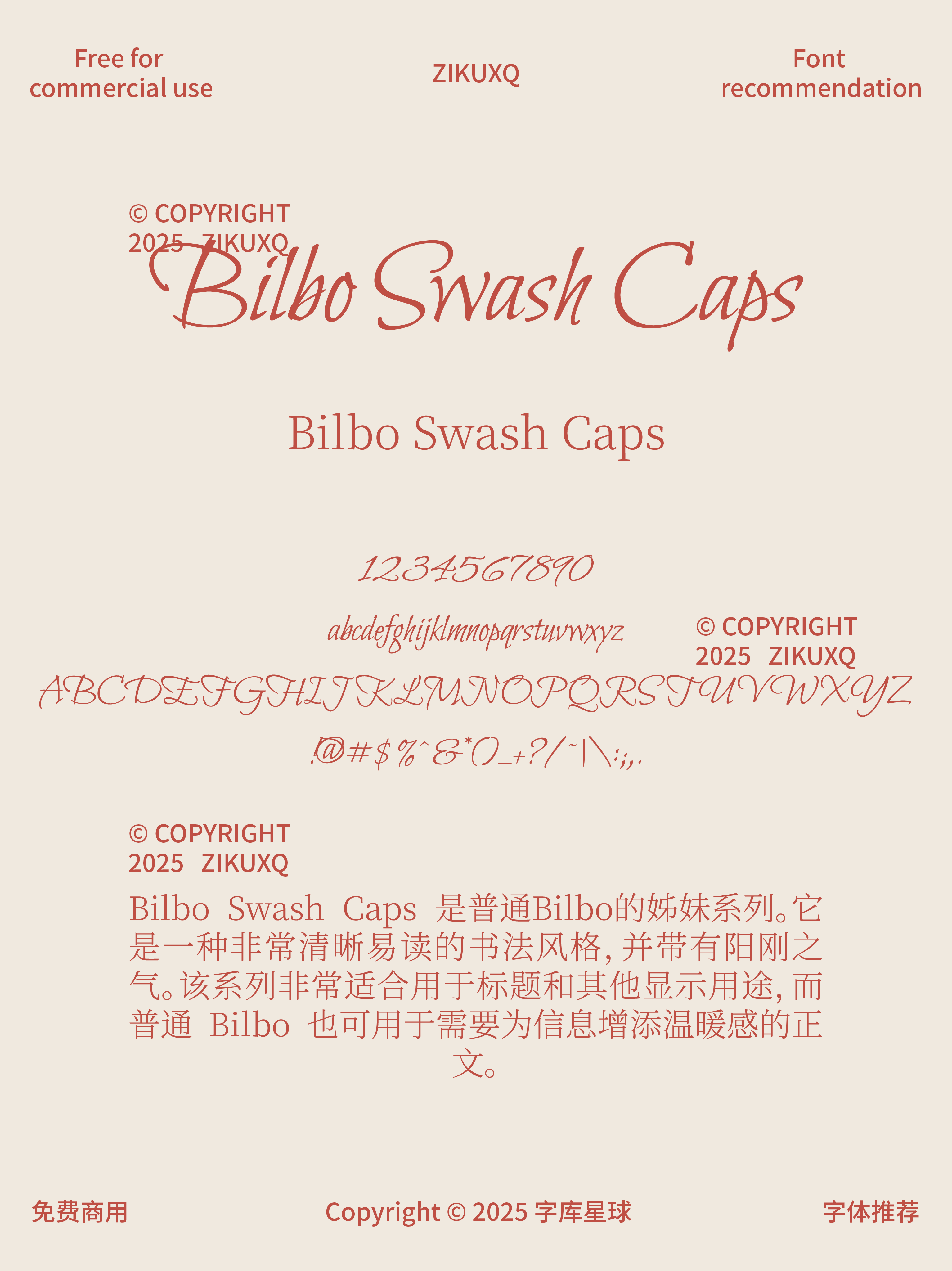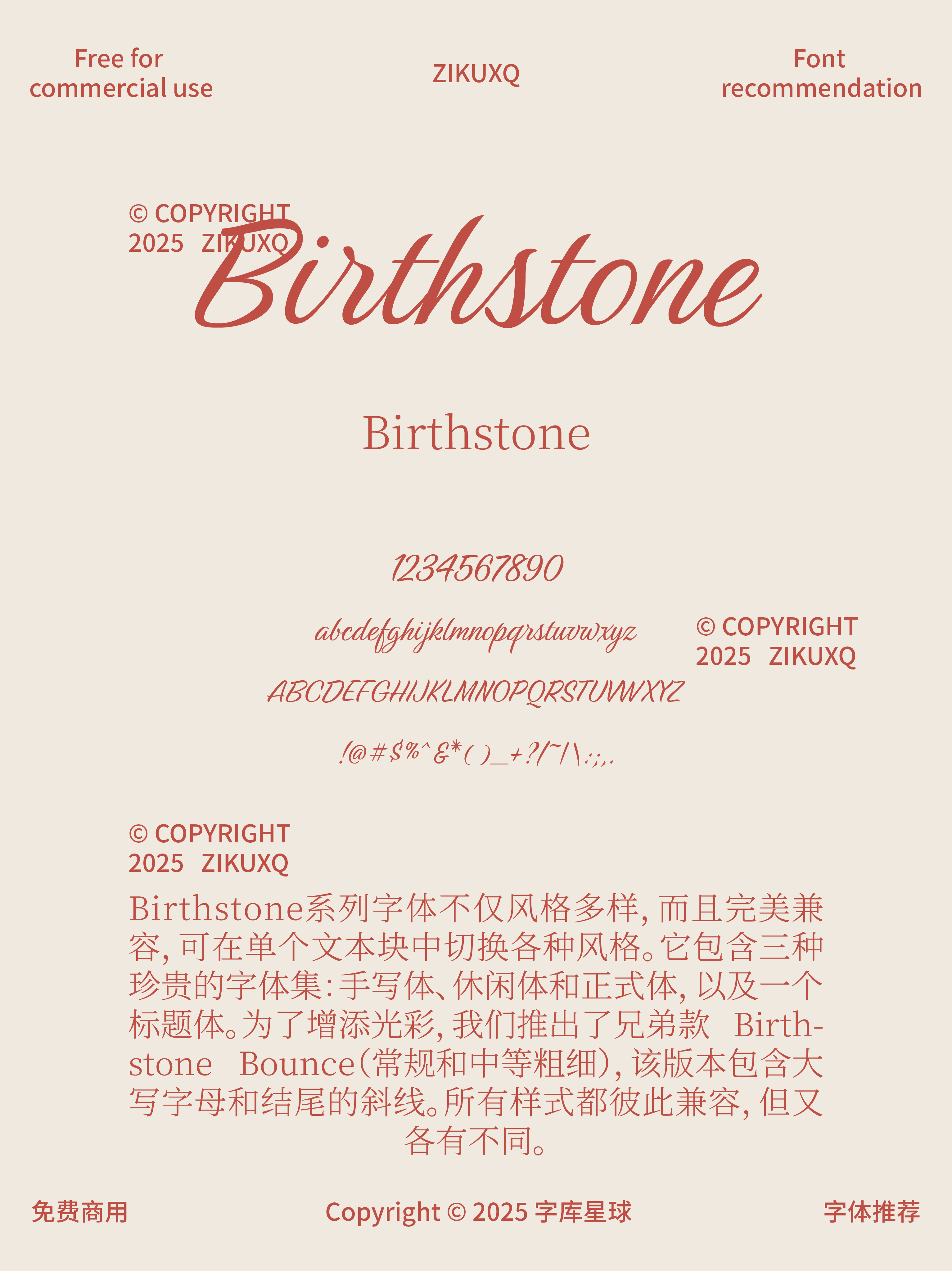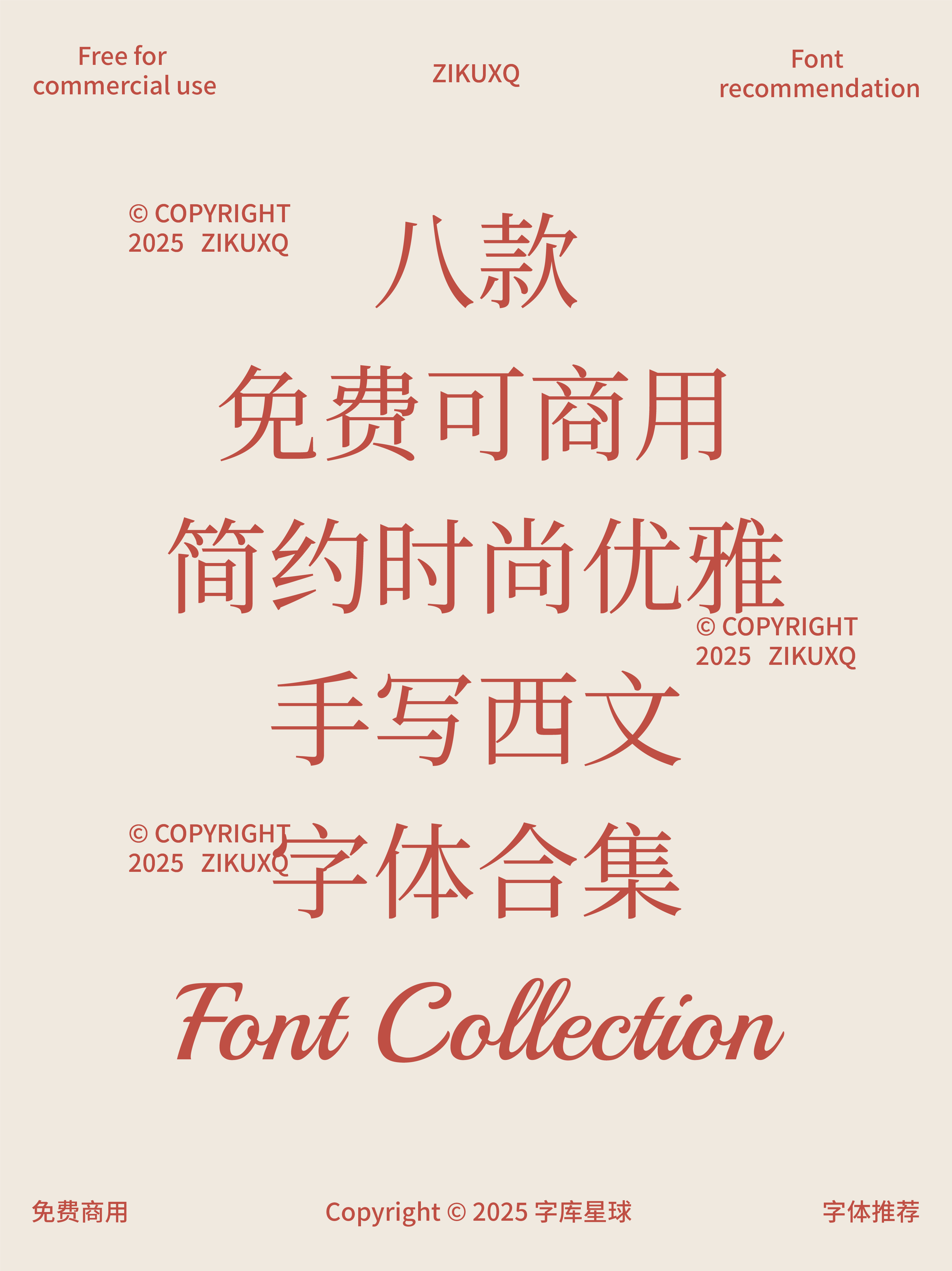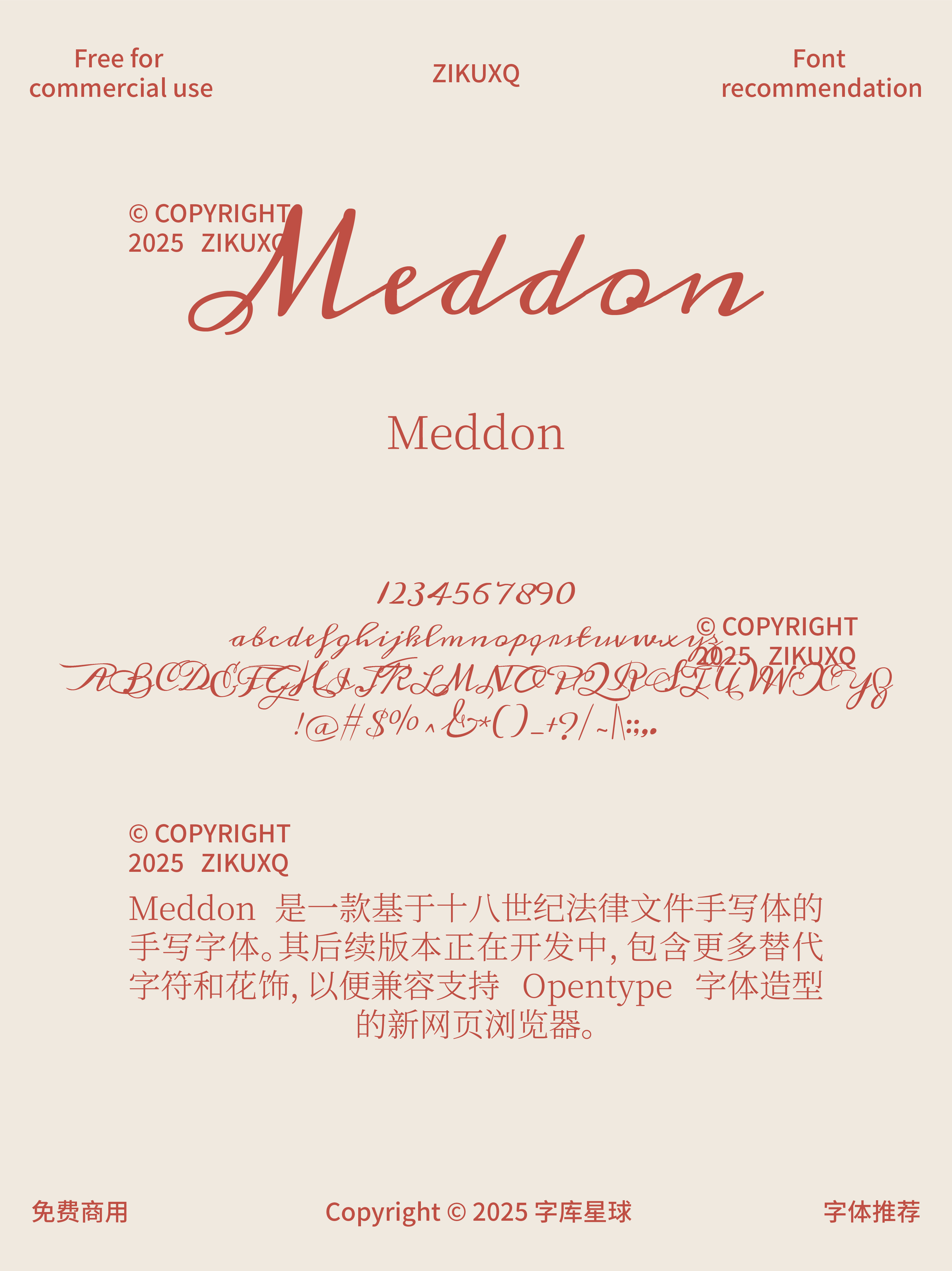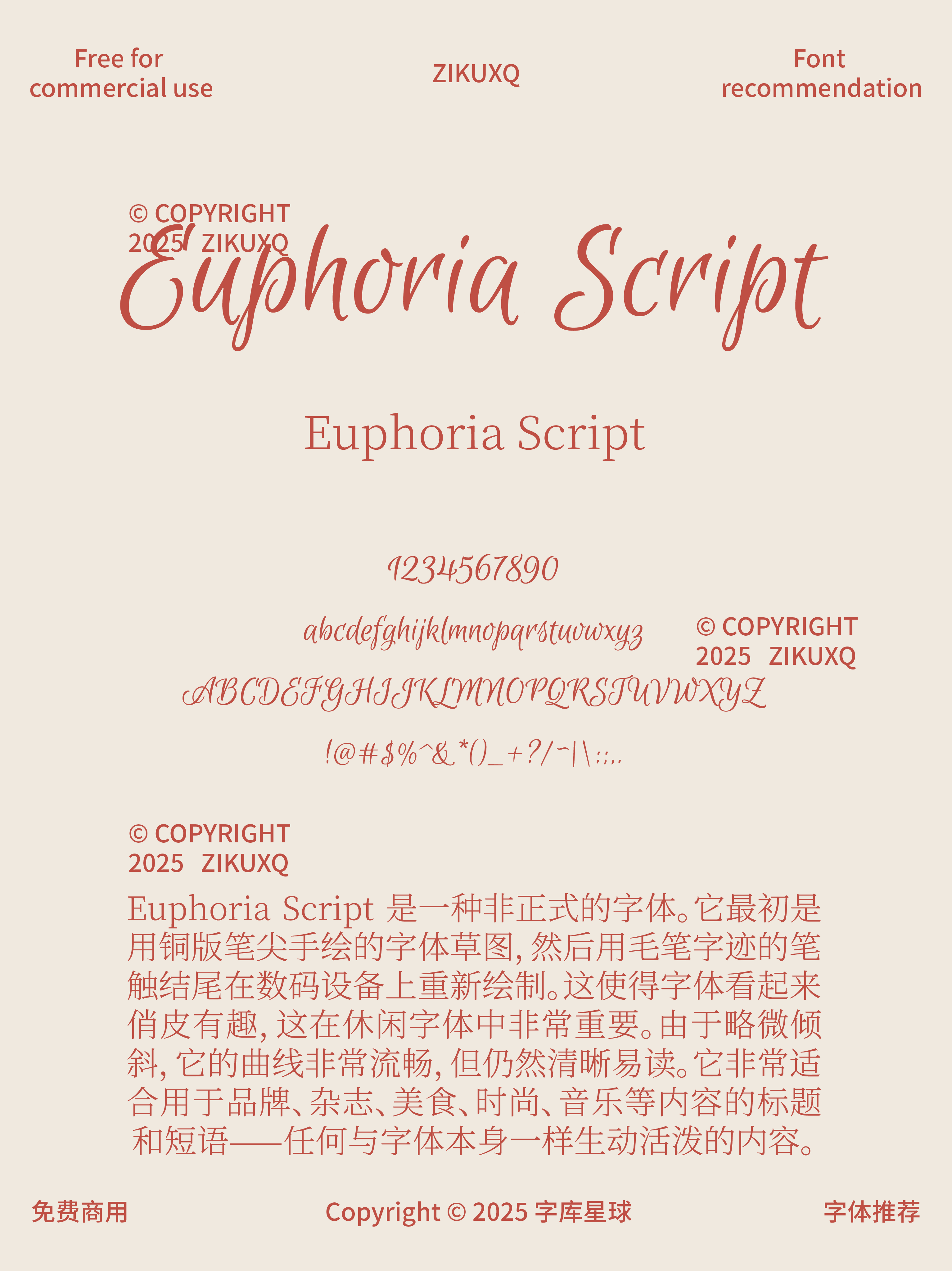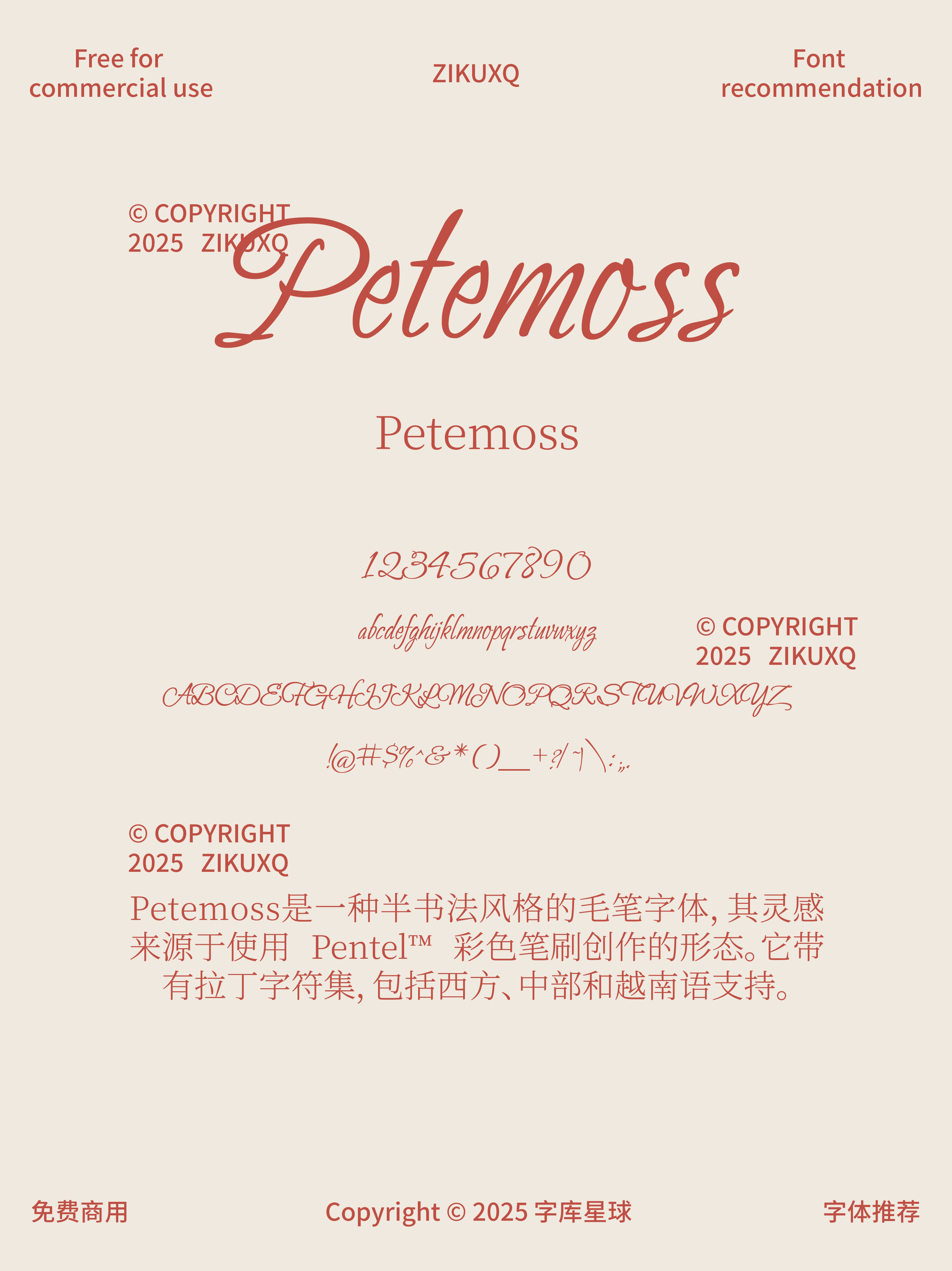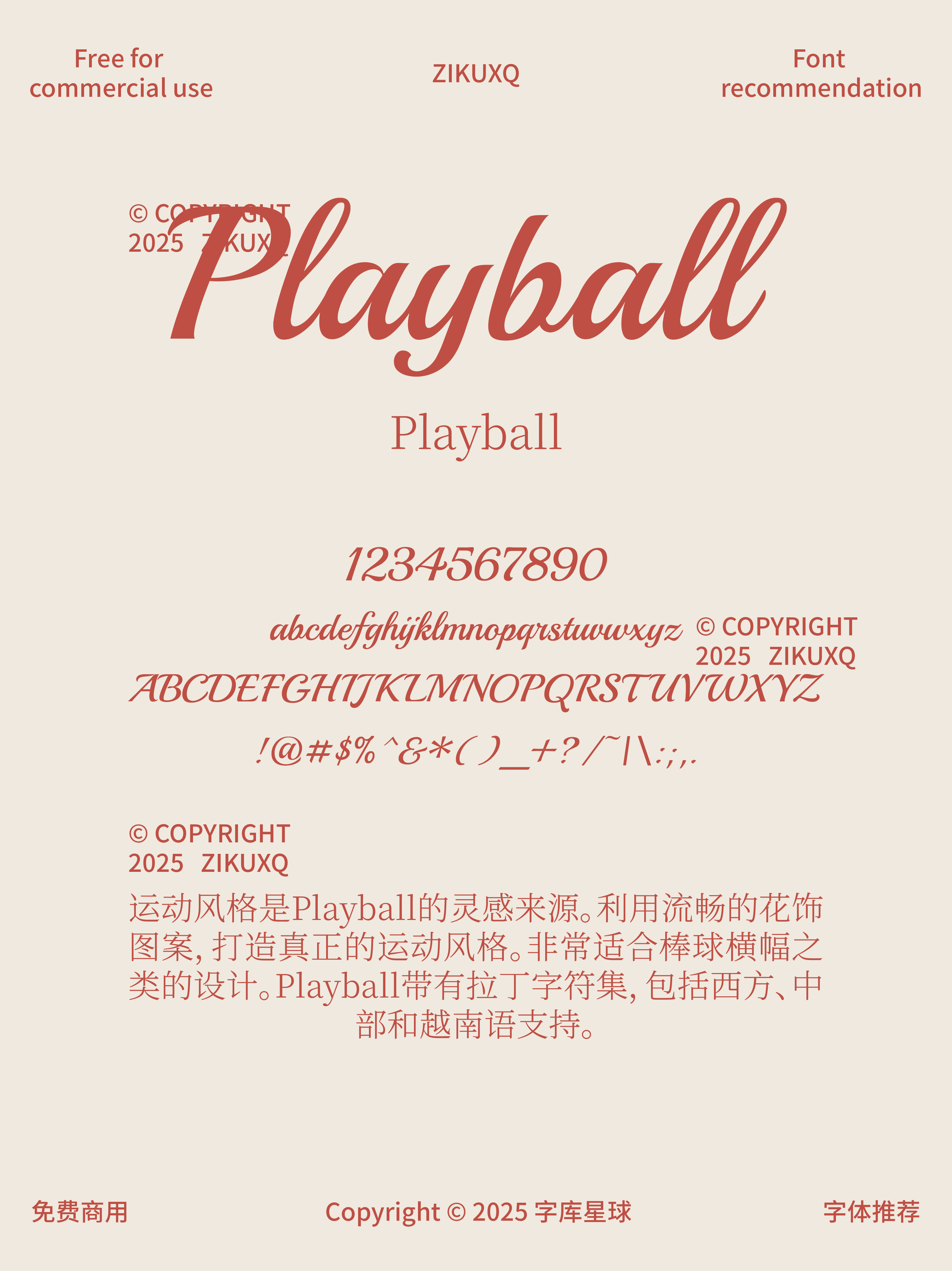
八款免费可商用简约时尚优雅手写西文字体
字体是设计的灵魂,一款好的字体能瞬间提升作品格调。今天给大家分享 8 款免费可商用的简约时尚优雅手写西文字体,拯救你的灵感枯竭。
手写的字体,线条流畅自然,充满灵动之美,有很好的识别性。适合文艺海报、书籍封面,营造浪漫氛围。
线条流畅且富有变化,简约中透着优雅。适合时尚杂志标题、时尚品牌广告,展现时尚品味。线条柔美,有手写的随性,又不失精致。用于美妆产品包装、情感类文案配图,十分吸睛。